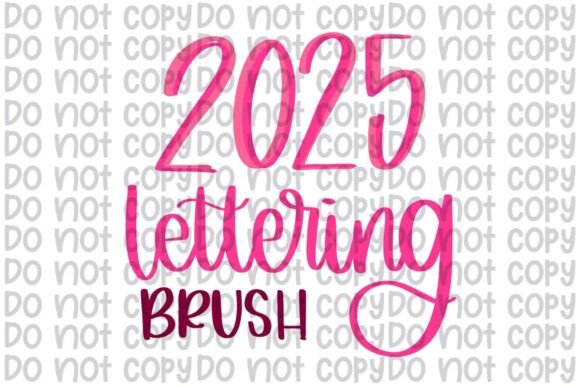
2025 Procreate Lettering Brush
Vous cherchez la brosse de lettering parfaite pour votre prochaine création Procreate ? Ne cherchez plus : le 2025 Procreate Lettering Brush est l’outil ultime pour libérer votre créativité. Conçu pour allier élégance et praticité, ce pinceau numérique offre une expérience de calligraphie fluide, intuitive et totalement adaptée aux artistes modernes.
Pourquoi le 2025 Procreate Lettering Brush fait sensation
- Pression sensible et douceur inégalées : chaque trait réagit à votre stylus comme s’il était un vrai pinceau, garantissant des lignes fines et des empattements impeccables.
- Calligraphie sans effort : le design précis de la brosse élimine le stress de la recherche manuelle, vous permettant de concentrer votre énergie sur l’inspiration.
- Qualité professionnelle : les formes qui se créent sont nettes, même à haute résolution, idéales pour les projets d’affichage, de branding ou de typographie artistique.
Que vous soyez designer, illustrateur ou amateur passionné, ce pinceau vous aidera à créer des lettres qui captivent et inspirent. Ajoutez le 2025 Procreate Lettering Brush à votre arsenal créatif aujourd’hui et découvrez la différence qu’une brosse bien conçue peut faire.